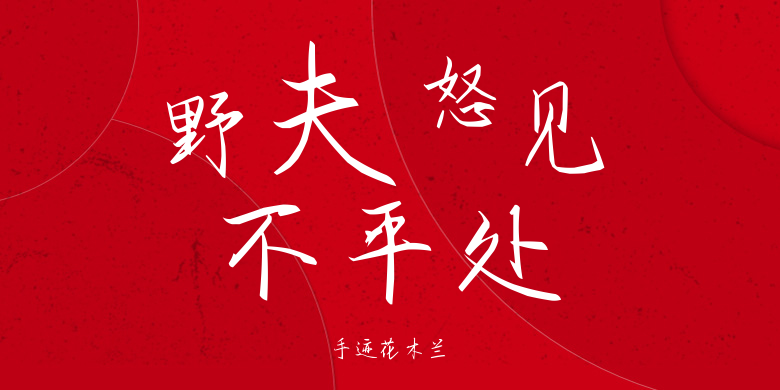
手迹花木兰
手迹花木兰,这款字体结构工整、笔画清晰,兼顾美观与易读性,适用于标题、正文、海报、包装、LOGO 等多种场景。字形优雅稳定,风格百搭耐看,适配日常排版与创意设计,让文字呈现更舒适、更具质感。手迹花木兰一笔一画,皆是细节,以均衡的比例、流畅的线条打造舒适视觉体验,字形端正大气,风格简约现代。无论是商业设计、品牌宣传还是日常排版,都能轻松驾驭,让文字更有格调与力量。手迹花木兰字体下载。